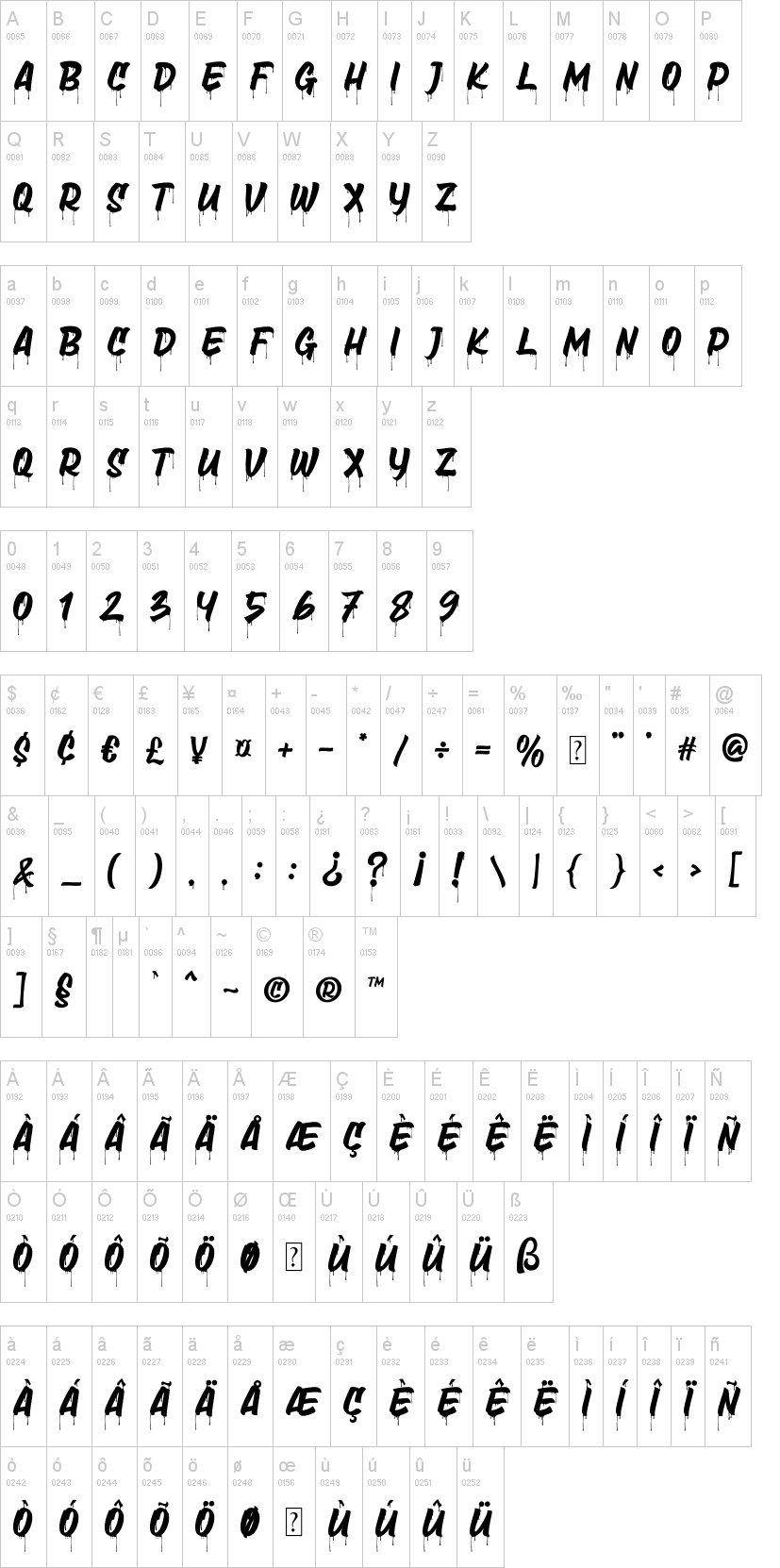
Death Markers
Death Markers 是一款黑暗、恐怖的字体,它可以用于许多不同的场景,从恐怖电影到游戏,甚至是海报和宣传物料。它的字形具有粗糙的质感,整体风格极具恐怖气息,可以让文字变得更加震撼而有力。
Death Markers是一款非常不错的手写艺术字体,具有很好的视觉感,适合于文化类的宣传设计、商业类品牌的广告和产品包装设计以及个性化文字排版等较多场景。
Death Markers字符映射图